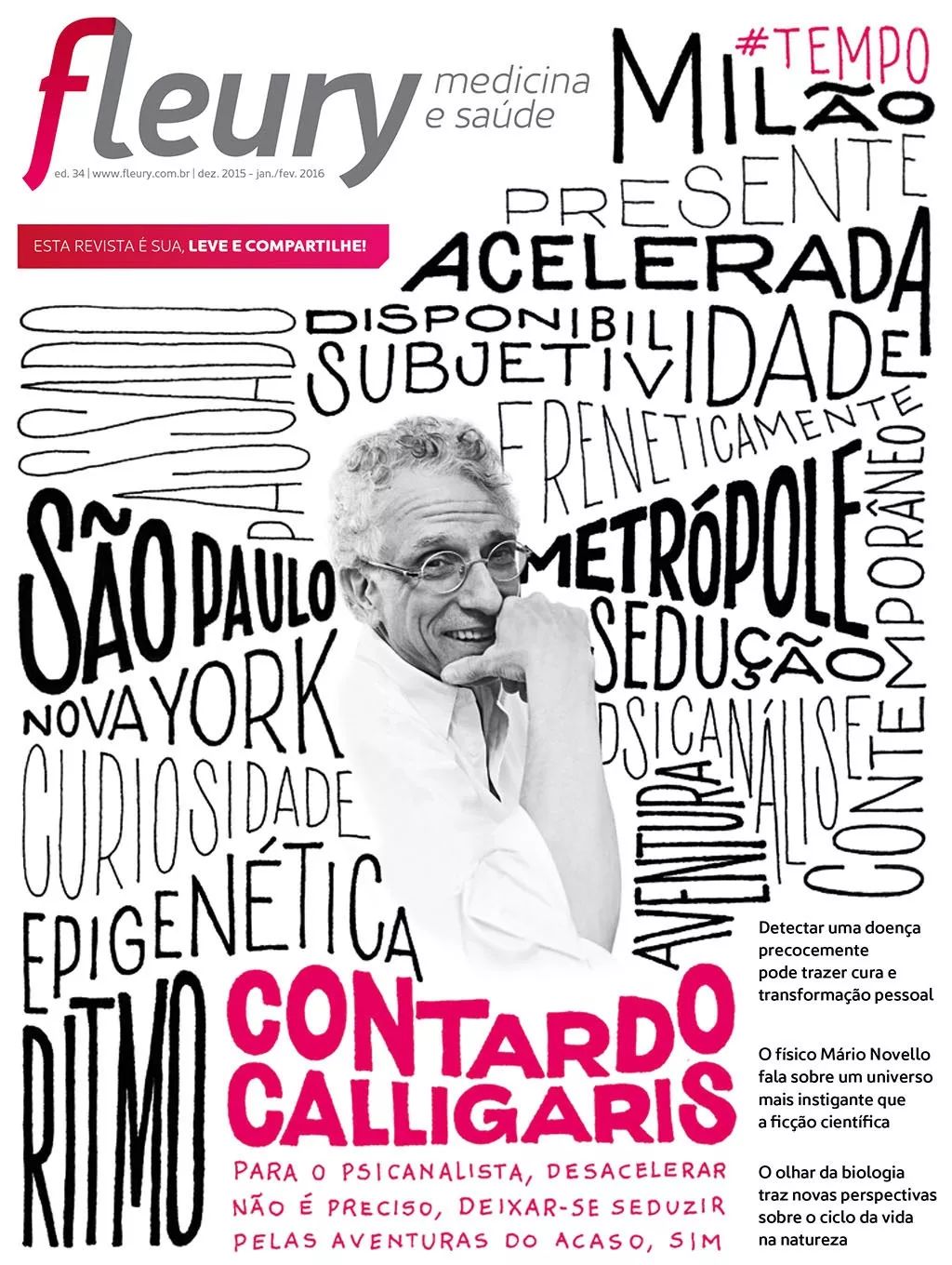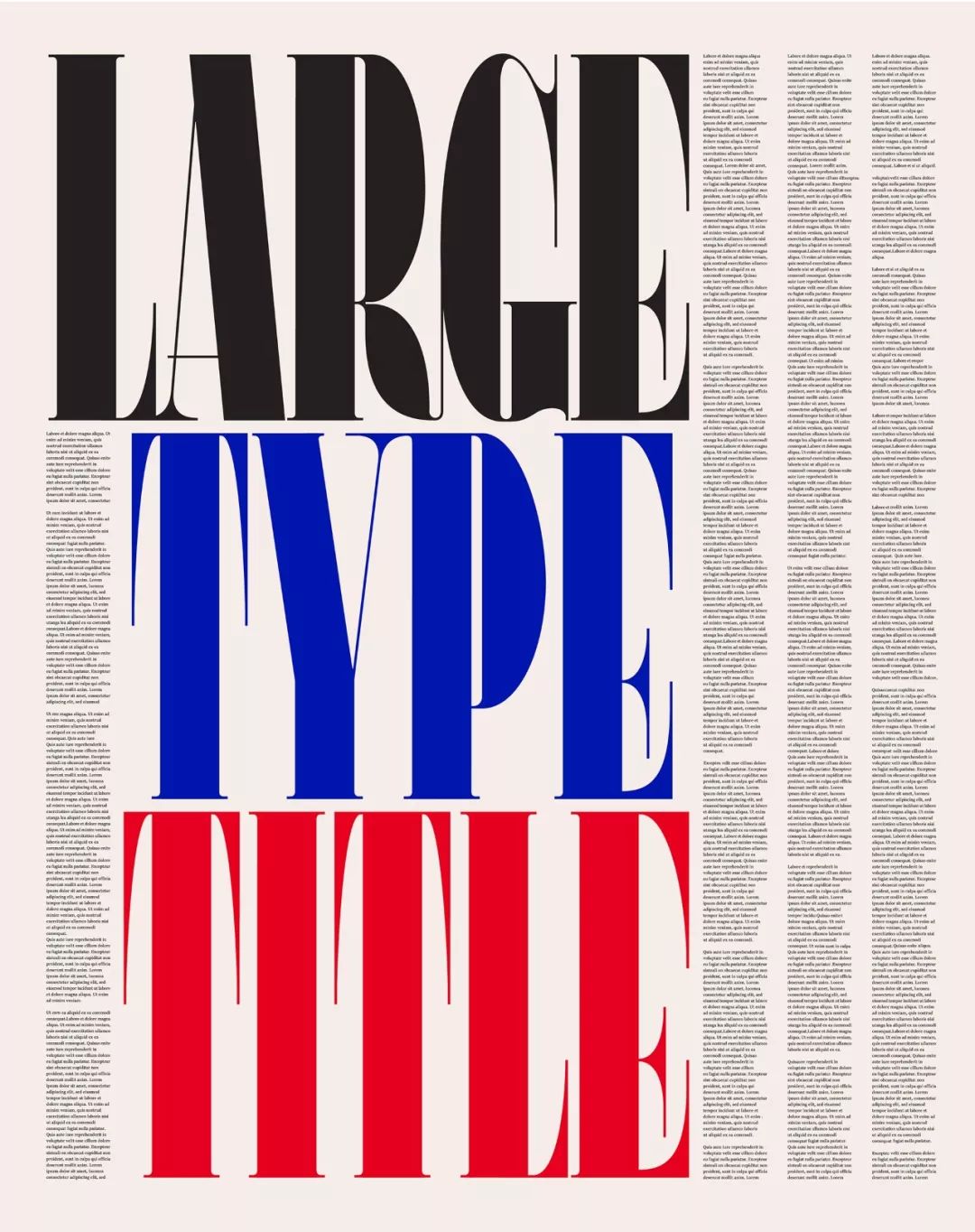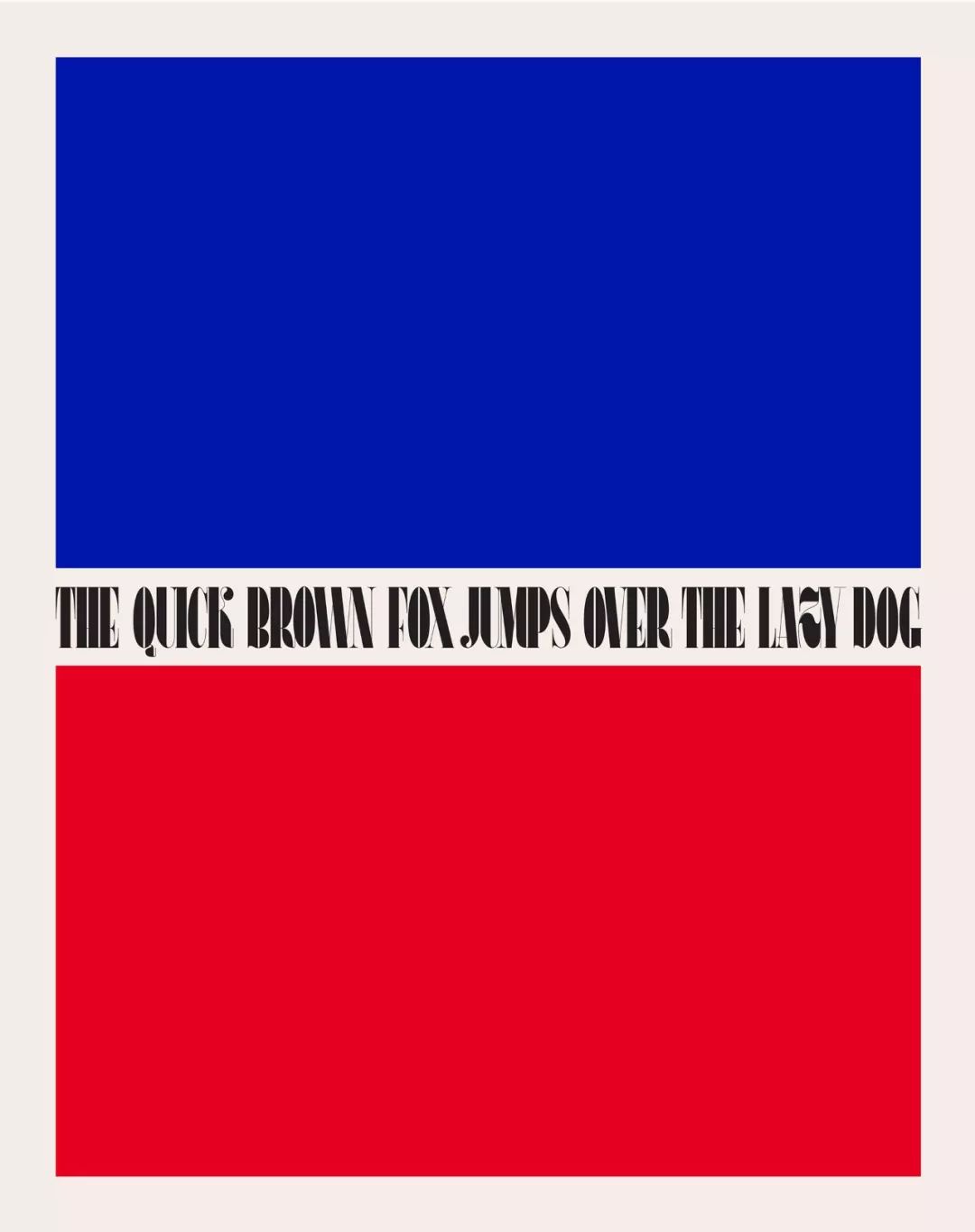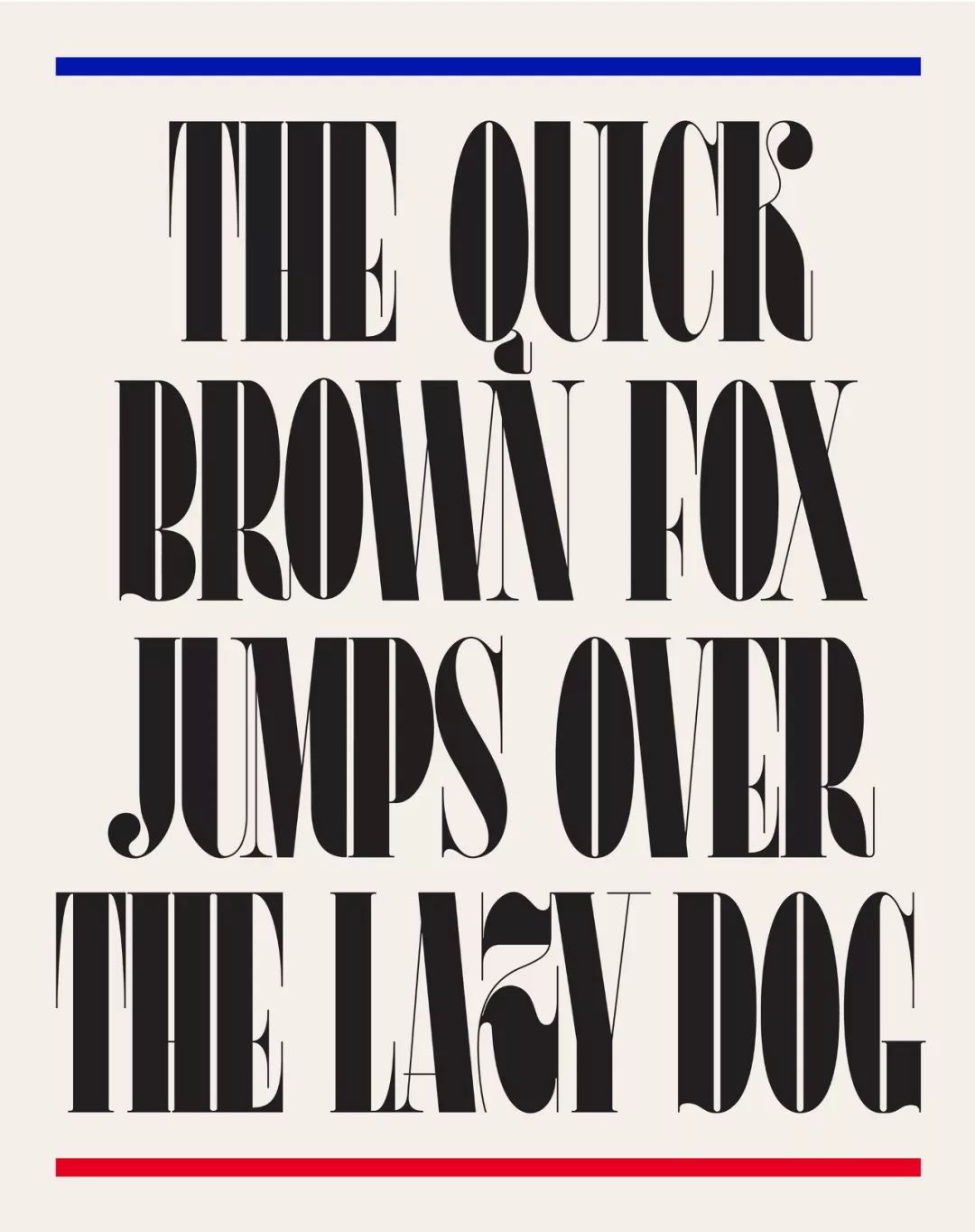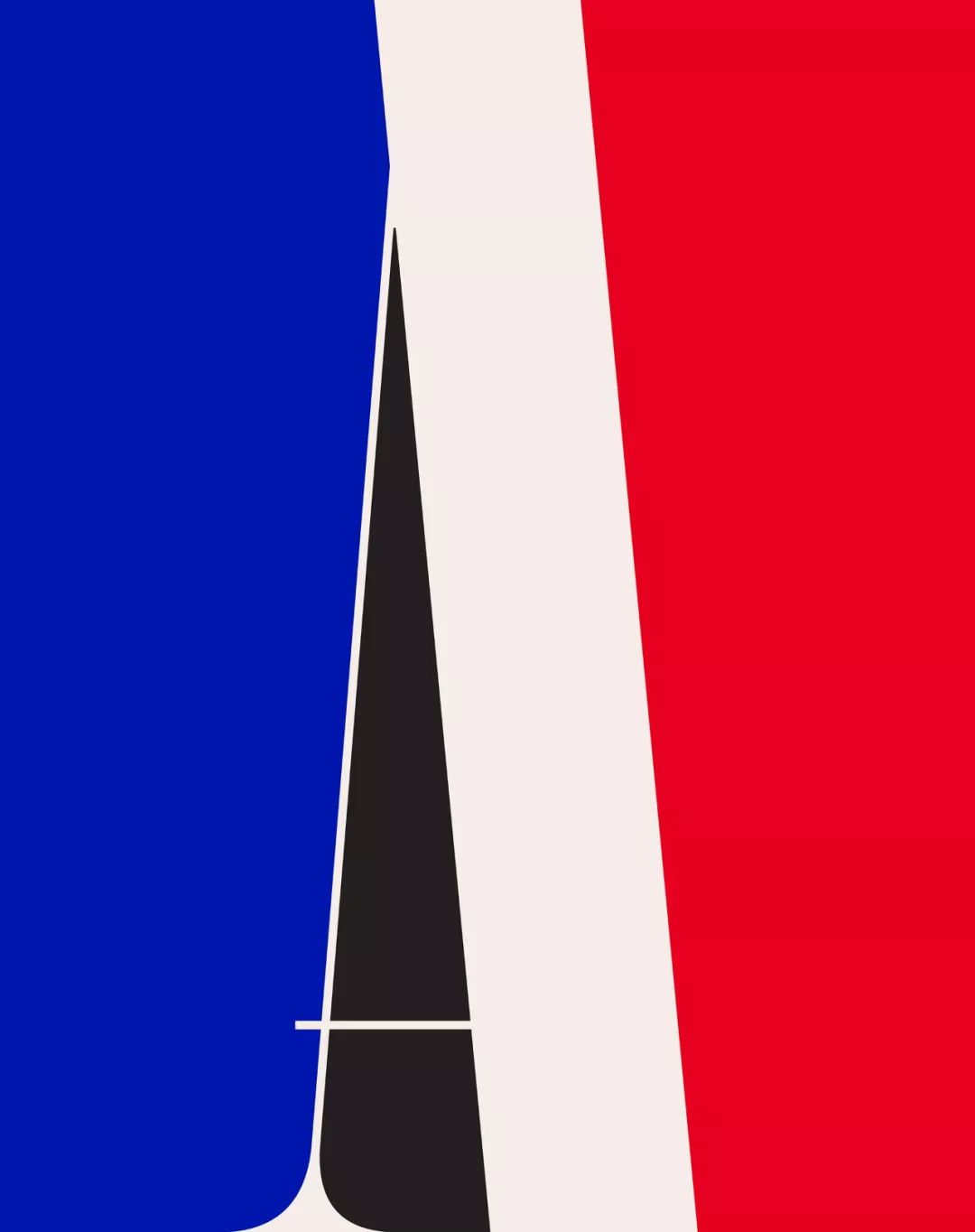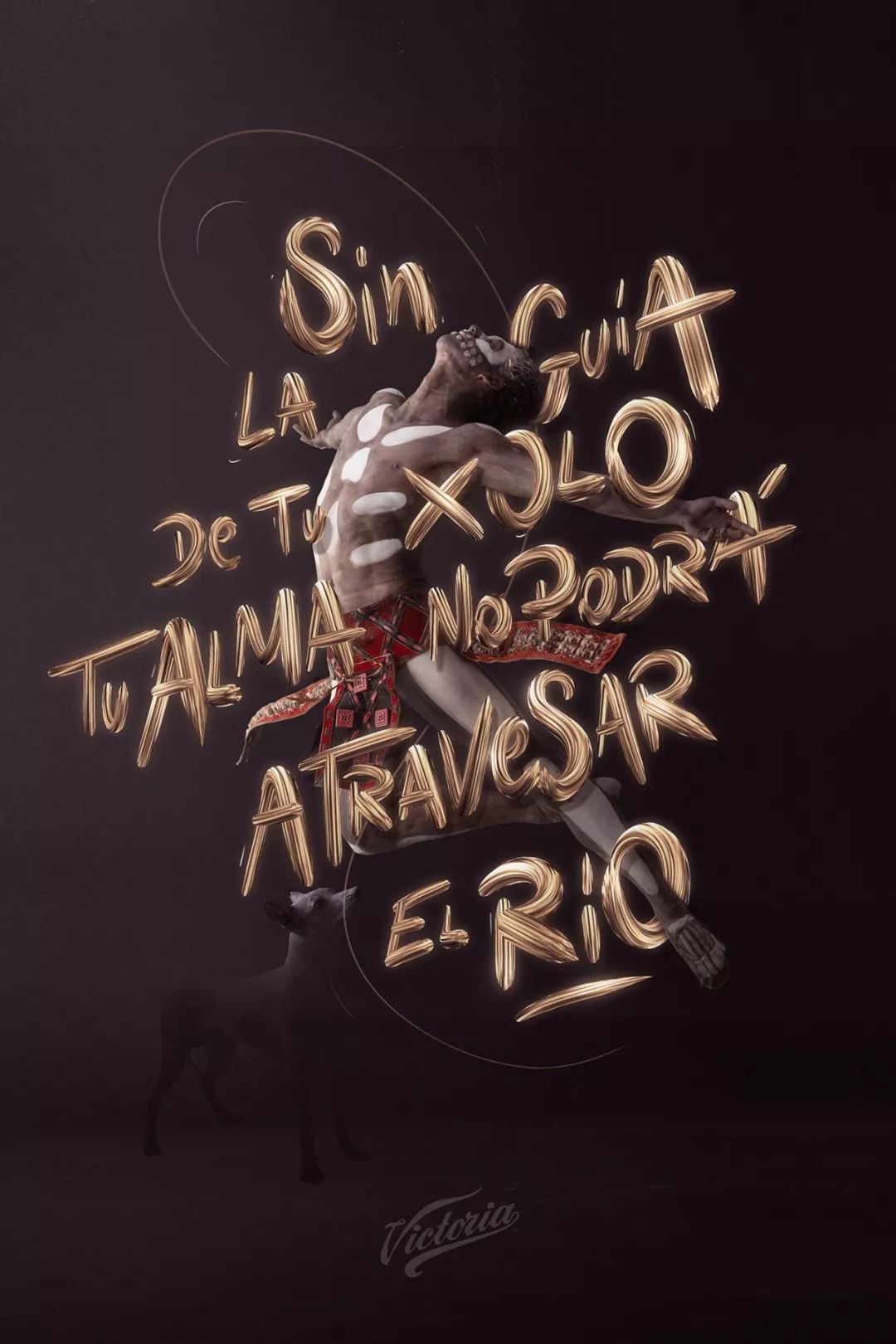
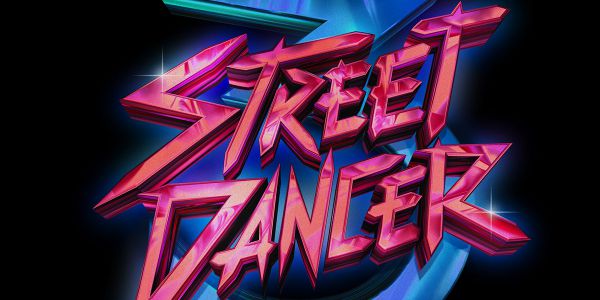
Behance上这10位荷兰设计师,字体好看到起飞~
今天柚子带你走进现代设计起源地之一的荷兰,看看他们是怎么将艺术和商业完美融合,behance大神我来啦!
Marina Chaccur
Marina Chaccur是一个自由职业者,在过去的13年里,她对印刷术、书法、字体设计都有尝试,还有最重要的一点:lettering!
作品:Handmade cards
作品:Fleury magazine cover
Wibke Bfeld
Wibke Bfeld 24岁,是一个多学科的设计师。
作品:The Future of our Consumer Society
作品:Istanbul
作品:konsumtion sverige
作品:Freedom of press
Nono Courtois
这是一个全能型的设计师,平面设计,编辑设计,视觉识别,品牌,字体设计,网页设计,前端开发都有涉及。
作品:Body Media ll Catalogue 身体媒体
作品:BlankPoster
Marijke Buurlage
Marijke Buurlage一直担任自由插画师,主要为杂志、儿童读物、书籍封面、海报、应用程序和电子书制作插图,也喜欢自己发起的项目。她的作品明亮、有趣、多彩、女性化。
作品:Beer Label Design
作品:Yoto Play
作品:农夫山泉茶包装
Tim Tijink
Tim Tijink,来自荷兰格罗宁根的自由平面设计师和艺术总监,工作领域包括:Branding / Identity / Typography / Art Direction。
作品:
Typography x Photography Poster SeriesTim
Marta Cerdà
Marta Cerdà 是一位阿姆斯特丹的独立艺术家、字体设计师、插画家和艺术总监。自2008年以来,她一直为国外的艺术、文化和广告客户工作。
作品:OMELET
作品:AFAR ALPHABET
作品:GOOP
Spencer Woolcott
Spencer Woolcott 是荷兰阿姆斯特丹的艺术总监、设计师和品牌传播专家。他以前是洛杉矶的营销和传播专业人士,现在经营着设计+品牌。
作品:Realm Global | Brand Identity
作品:Mindsticker | Brand Identity
作品:The New Form | Brand Identity
Tempo | Brand Identity
Clémence Gouy
Clémence Gouy是一个平面设计师和插画家,专注于品牌和视觉设计项目。
作品:PHILHARMONY — Poster Series
作品:Horoscope — Editorial Illustration
作品:Women in Visual Communication — Card Game
José Bernabé是一名设计师兼插画家,目前总部设在阿姆斯特丹市,他将印刷术、字体和插图结合到数字技术和传统技术中,通过生动多彩的艺术作品实现视觉解决方案。
作品:MAD COOL 2019
作品:CHINGONES HASTA EN LA MUERTE
作品:#Made of
作品:ALL DAY BREAK-FEAST
Thom Niessink
Graphic & Type Designer的平面和字体设计师,特别擅长字库字体开发。
作品:Bw Helder
作品:Chromoxome Pro - Typeface
Thom Niessink还创作了一款免费字体——FREE FAT FONT